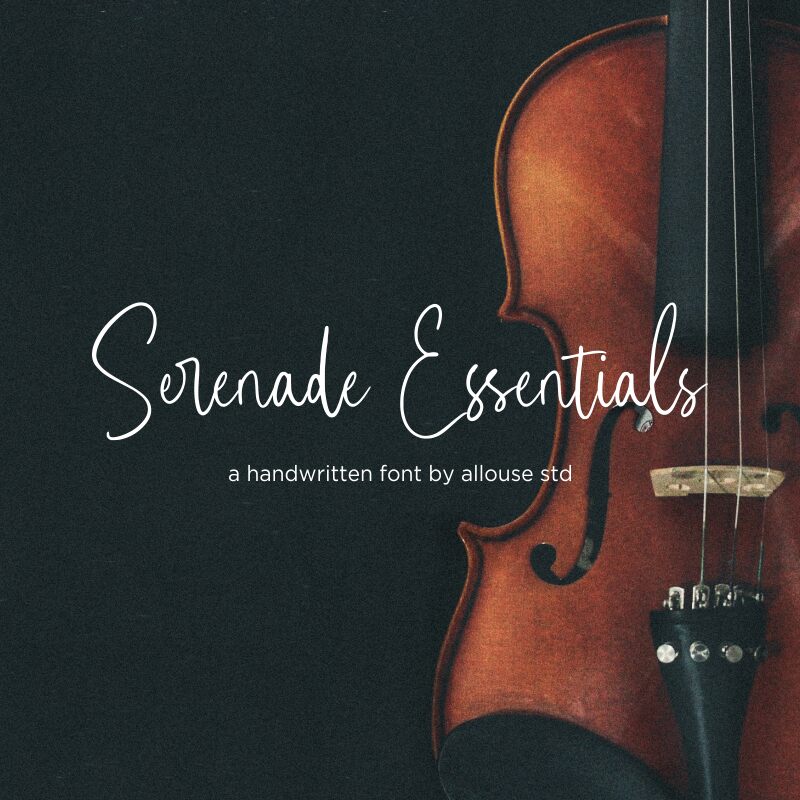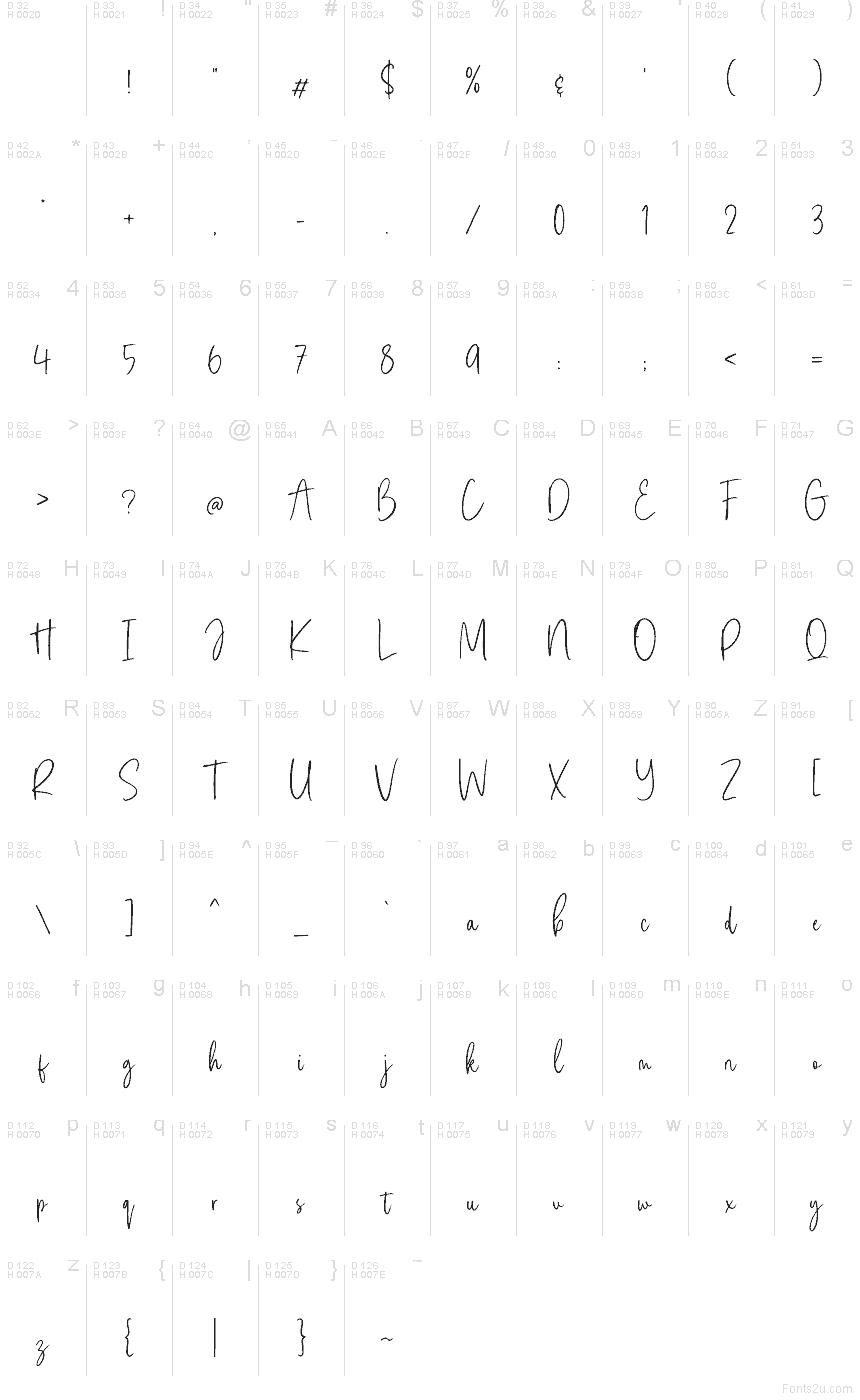
Serenade Essentials
Písmo Serenade Essentials od Allouse.Studio je bezplatné ručne písané písmo s dlhými, prepojenými ťahmi a jemným, ležérnym rytmom. Písmená pôsobia otvorene a vzdušne, s úzkymi tvarmi, ktoré vyzerajú, akoby boli nakreslené jedným plynulým pohybom, a nie vyskladané zo statických prvkov.
Serenade Essentials sa skvele hodí na svadobné oznámenia, pozdravy, podpisy v logách, grafiku s citátmi, príspevky na sociálne siete či jemné balenia produktov, pretože jeho voľná ručná linka dodáva textu osobný, autentický nádych. Toto bezplatné písmo sa výborne hodí aj ako dizajnový akcent či pre krátke popisy v prípadoch, keď chcete dosiahnuť ľahký kaligrafický vzhľad bez pocitu formálnosti či ťažkopádnosti.